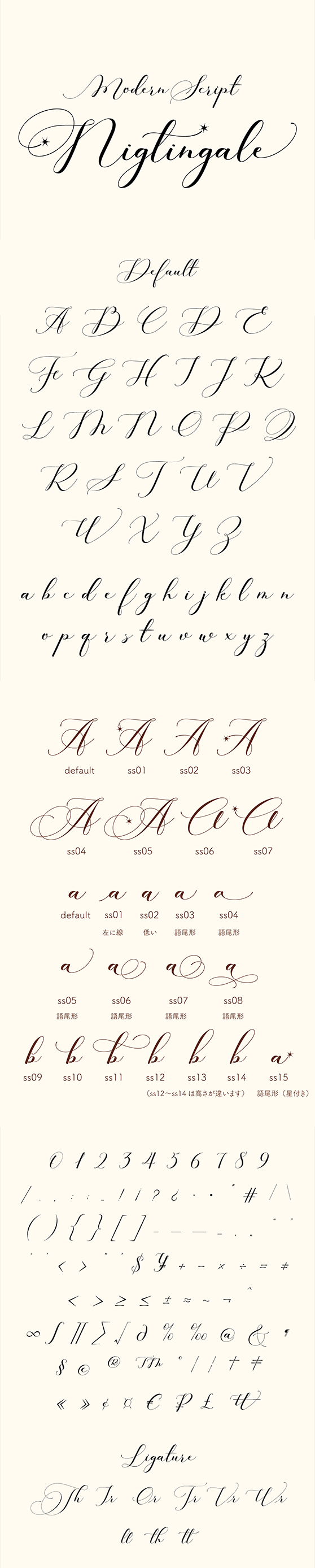
筆記体
Satsuyako
Nightingale
STYK_Nightingale
夜に歌う小鳥の歌声をイメージしたモダンスクリプト体です。小文字の高さ・大きさが不揃いでリズム感が出るようになっています。
ひとつのフォントファイルの中に、デフォルト字形 + 異体字(大文字7種類、小文字の異体字16種類)を収録しています。
・基本ラテン文字
・ラテン文字( 一部 )
・結合分音記号 ( 一部 )
・約物
・記号類 ( 一部 )
・大文字の異体字ss01~ss07
・小文字の異体字ss01~ss16
・リガチャ